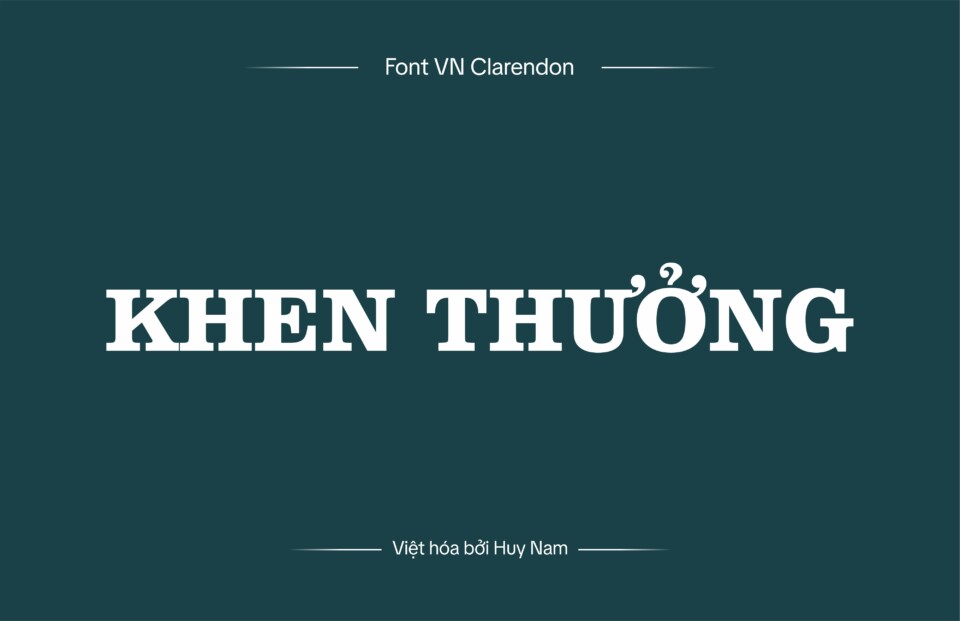
Font Việt hóa VN Clarendon
Font Việt hóa VN Clarendon – Lựa chọn Serif cổ điển và chuyên nghiệp cho thiết kế
Trong thế giới thiết kế đồ họa tại Việt Nam, việc lựa chọn một bộ Font Miễn Phí chất lượng luôn là ưu tiên hàng đầu của các bạn học sinh và giáo viên. Font Việt hóa VN Clarendon nổi lên như một biểu tượng của sự kết hợp hoàn hảo giữa nét cổ điển phương Tây và sự tinh tế trong cách xử lý dấu tiếng Việt. Đây là bộ phông chữ thuộc họ Slab Serif, nổi bật với các chân chữ dày và những đường nét mạnh mẽ, tạo nên cảm giác tin cậy và chuyên nghiệp cho mọi bản thảo học thuật hay sản phẩm truyền thông trường học.
Nguồn gốc và đặc điểm nổi bật của Font Việt hóa VN Clarendon
Bộ Font Việt hóa VN Clarendon vốn dựa trên nguyên mẫu Clarendon gốc được ra đời từ thế kỷ 19 tại Anh. Khi được chuyển ngữ và tối ưu hóa cho bảng mã Unicode tiếng Việt, nó vẫn giữ trọn vẹn những đặc trưng hình khối rõ rệt nhưng lại vô cùng mềm mại ở các góc bo tròn. Điều này giúp bộ chữ không bị thô cứng, mang lại cái nhìn thiện cảm cho người xem ngay từ lần đầu tiên tiếp xúc trên các trang bìa giáo án hay biểu ngữ sự kiện.
Ưu điểm của font chữ trong trình bày văn bản
Lý do khiến Font Việt hóa VN Clarendon được yêu thích chính là độ tương phản trung bình, giúp người đọc không bị mỏi mắt khi theo dõi các đoạn văn dài. Các ký tự tiếng Việt được thiết kế tỉ mỉ, đảm bảo các dấu thanh như huyền, sắc, hỏi, ngã, nặng được đặt đúng vị trí, không bị đè lên chữ hay làm mất khoảng cách dòng tự nhiên. Đối với các em học sinh đang làm bài tập thuyết trình, bộ font này giúp các tiêu đề trở nên nổi bật và có sức nặng về mặt thị giác.
Ứng dụng Font Việt hóa VN Clarendon trong giáo dục và sáng tạo
Không chỉ giới hạn trong các thiết kế thương mại, Font Việt hóa VN Clarendon còn là công cụ đắc lực cho môi trường giáo dục. Giáo viên có thể sử dụng font này để thiết kế các chứng chỉ khen thưởng, bằng khen vì nó mang lại vẻ trang trọng và truyền thống. Sự vững chãi của từng con chữ giúp khẳng định giá trị của nội dung mà người soạn thảo muốn truyền tải, đồng thời tạo ra một phong cách trình bày đồng nhất và khoa học cho các tài liệu nội bộ.
Cách phối hợp font chữ hiệu quả
Để đạt hiệu quả thẩm mỹ cao nhất, bạn nên kết hợp Font Việt hóa VN Clarendon với một bộ font không chân (Sans Serif) hiện đại cho phần nội dung chi tiết. Sự đối lập giữa sự mạnh mẽ của Slab Serif ở tiêu đề và sự thanh thoát của Sans Serif ở thân bài sẽ tạo nên một bố cục hài hòa, dễ nhìn. Điều này cực kỳ quan trọng khi các bạn học sinh cần trình bày các dự án nghiên cứu khoa học hoặc báo cáo thực tập sao cho chuyên nghiệp nhất.
Kết luận về bộ phông chữ VN Clarendon